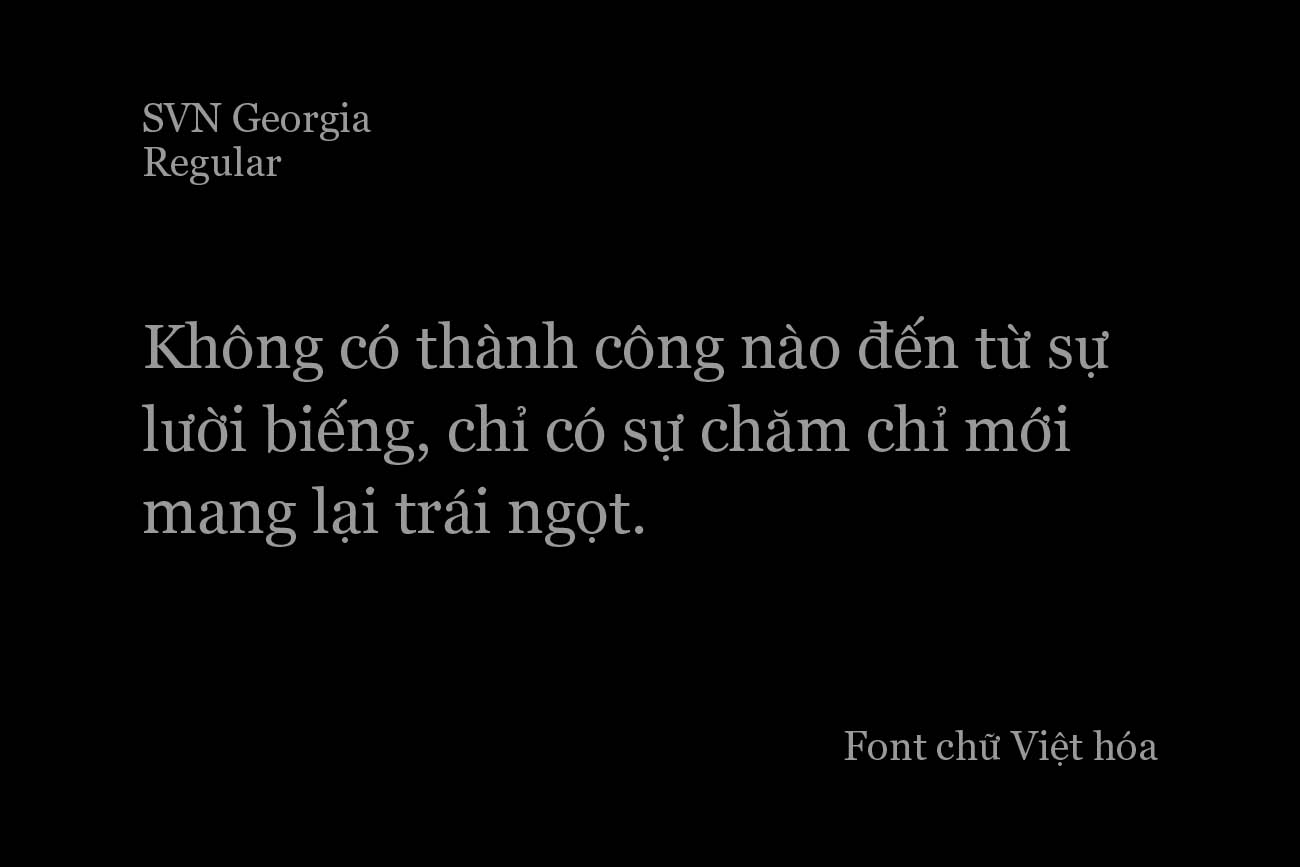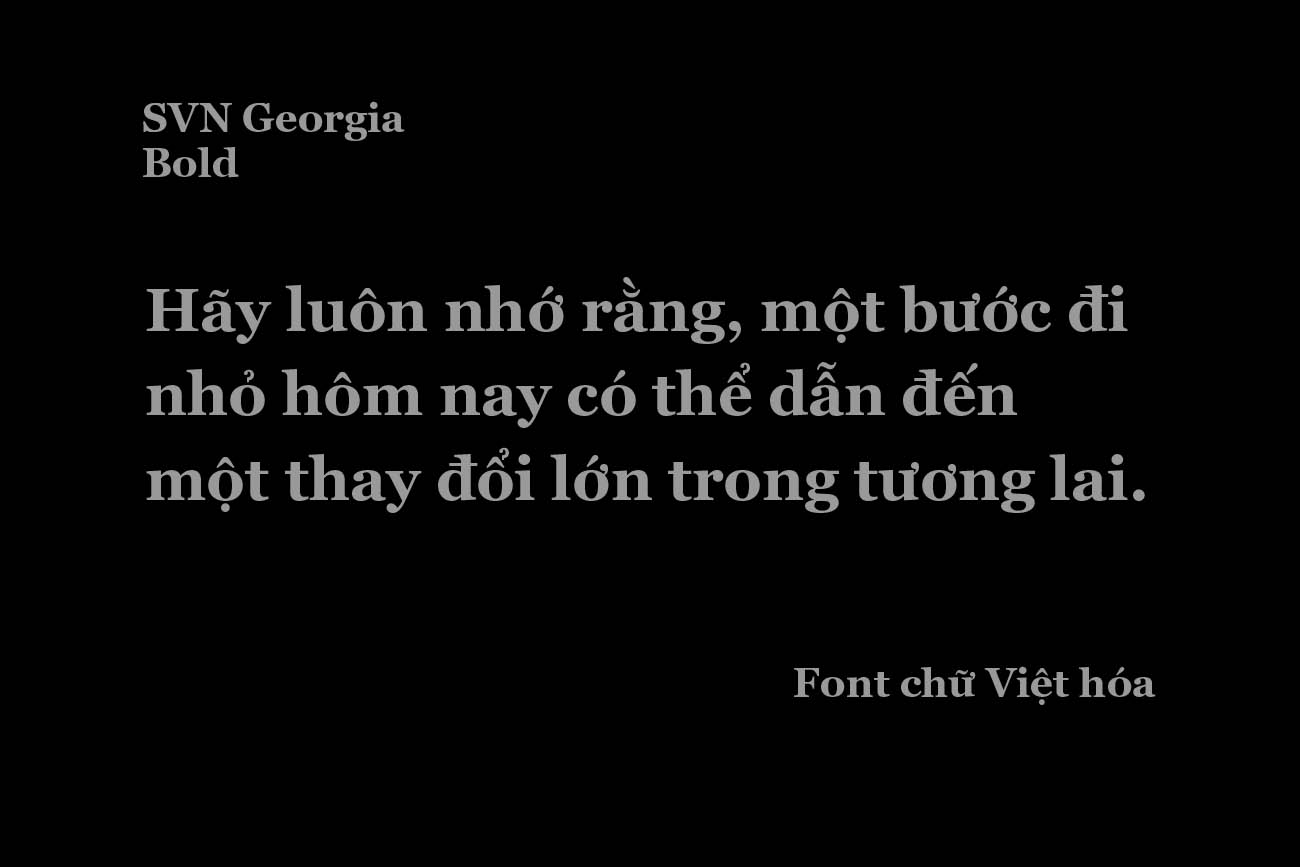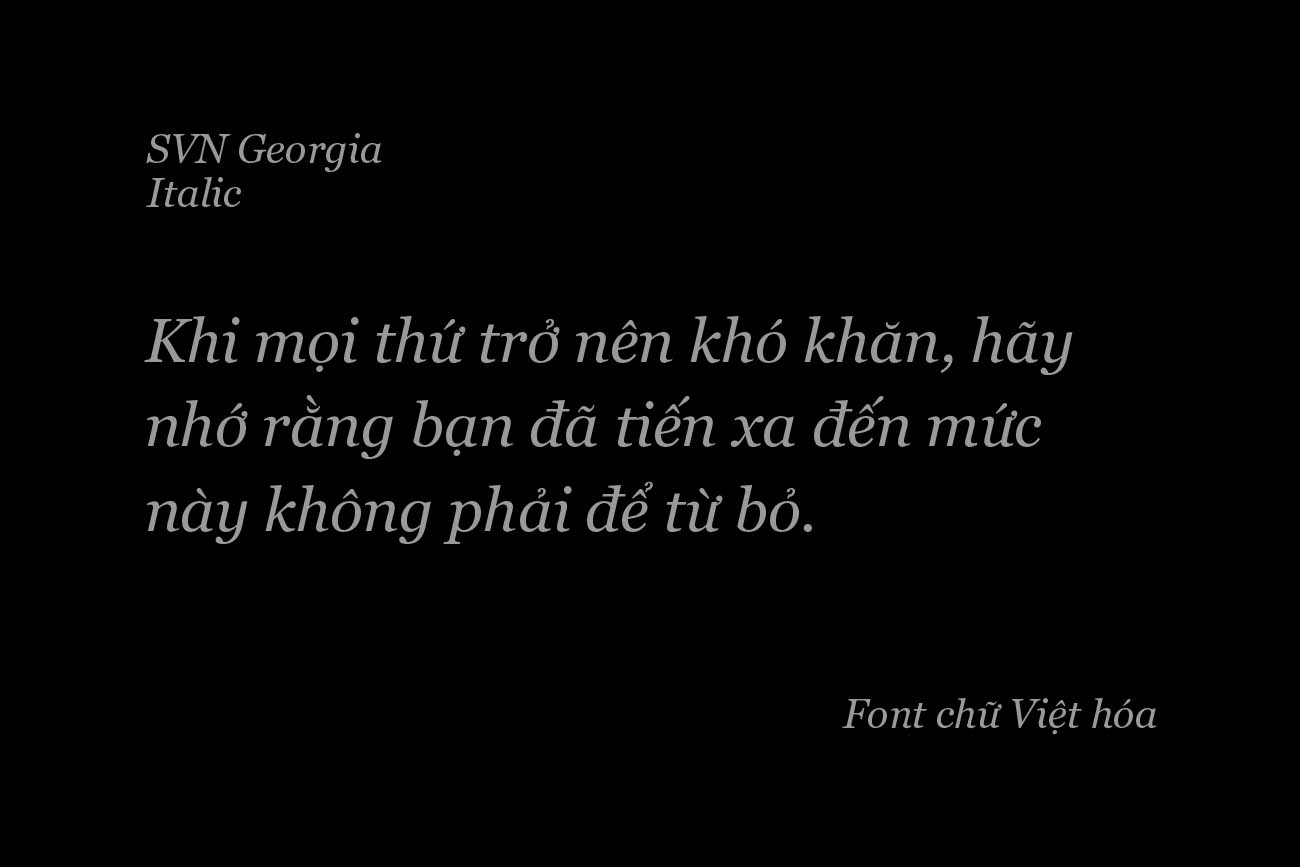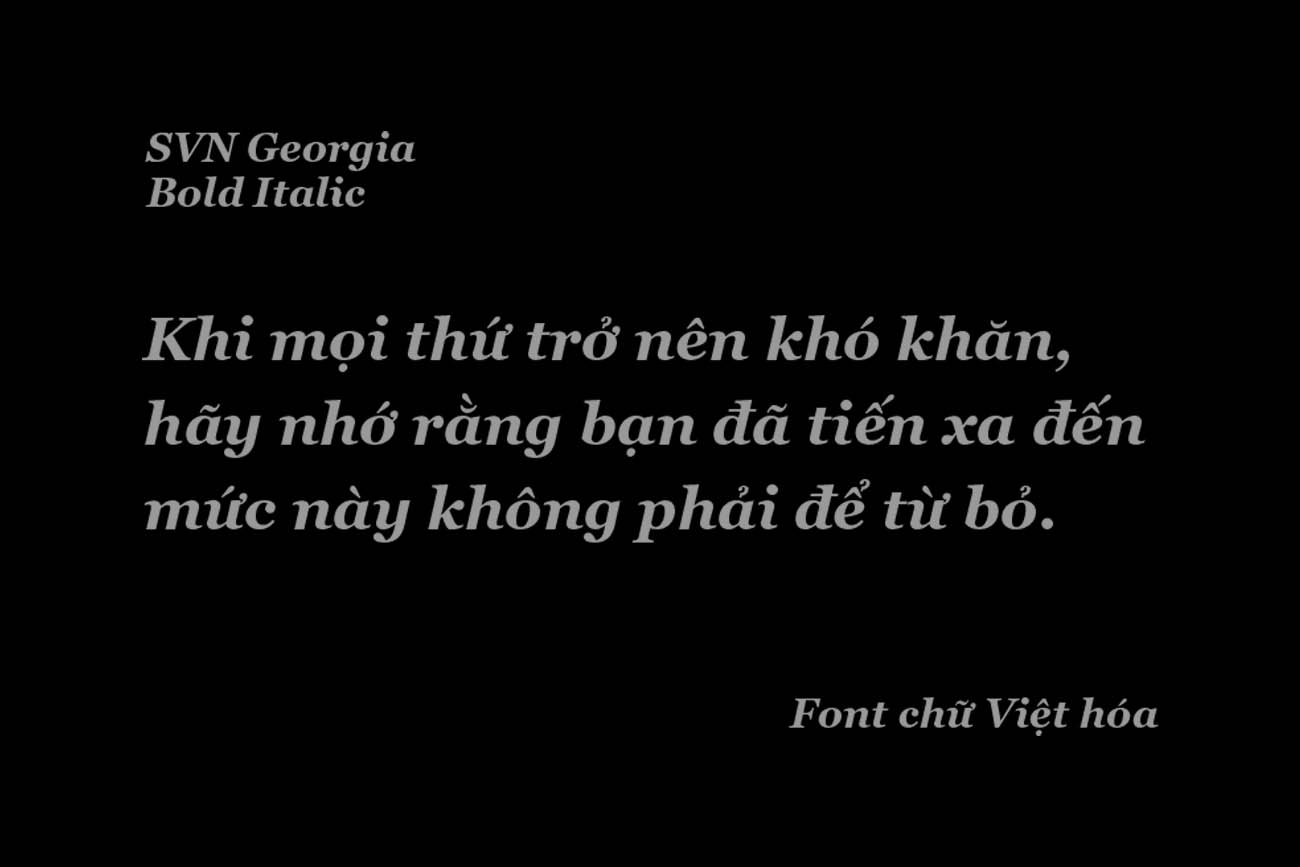
Tác giả Matthew Carter
Việt hóa Team SVN
SVN-Georgia là phiên bản Việt hóa của font chữ Georgia – một trong những serif typeface kinh điển nhất trong thế giới thiết kế. Với đường nét thanh lịch, dễ đọc và tối ưu cho màn hình máy tính, SVN-Georgia là lựa chọn hàng đầu dành cho những ai đang tìm kiếm một font chữ chuyên nghiệp, cổ điển nhưng hiện đại, đặc biệt phù hợp cho văn bản dài và nội dung số.
Tác giả & Việt hóa:
Font gốc Georgia được thiết kế bởi Matthew Carter vào năm 1993 cho Microsoft, với mục tiêu chính là tạo ra một font serif có thể hiển thị rõ ràng ngay cả trên màn hình độ phân giải thấp. SVN-Georgia là bản Việt hóa được thực hiện bởi STYLEno.1 Fonts (SVN Fonts) – đơn vị nổi tiếng với hàng trăm font chữ Việt hóa chất lượng cao. Bản Việt hóa này hỗ trợ đầy đủ tiếng Việt, bao gồm dấu thanh, ký tự đặc biệt và các biến thể kiểu chữ như Regular, Italic, Bold, Bold Italic.
Đặc điểm nổi bật:
• Nét chữ thanh thoát, rõ ràng, dễ đọc ở cả cỡ chữ nhỏ lẫn lớn.
• Các chữ cái có độ đậm tương phản cao, giúp nổi bật nội dung mà không gây mỏi mắt
• Chân chữ mềm mại, cân đối giữa nét cổ điển và tính hiện đại, rất phù hợp với thiết kế nghiêm túc, chuyên nghiệp.
• Hỗ trợ tiếng Việt hoàn chỉnh, không lỗi ký tự, đảm bảo sử dụng tốt cho các tài liệu in ấn và kỹ thuật số.
Vì sao nên dùng SVN-Georgia?
SVN-Georgia là font chữ serif Việt hóa lý tưởng nhờ khả năng hiển thị rõ ràng, dễ đọc trên mọi thiết bị, kể cả màn hình nhỏ. Với đường nét thanh thoát, tương phản cao, font giúp mắt người đọc thoải mái ngay cả khi tiếp xúc với nội dung dài.
Thiết kế mang lại cảm giác chuyên nghiệp và chuẩn mực, phù hợp cho văn bản hành chính, tài liệu học thuật hay thuyết trình. Đặc biệt, SVN-Georgia được Việt hóa đầy đủ, không lỗi dấu, hiển thị trọn vẹn tiếng Việt. Bộ font gồm đầy đủ các biến thể như Regular, Italic, Bold và Bold Italic, cho phép sử dụng linh hoạt trong cả thiết kế in ấn lẫn trình chiếu kỹ thuật số. Dù dùng cho web, ebook, CV hay sách in, font luôn giữ được sự mạch lạc, rõ ràng và đáng tin cậy – rất phù hợp với người dùng chuyên nghiệp.